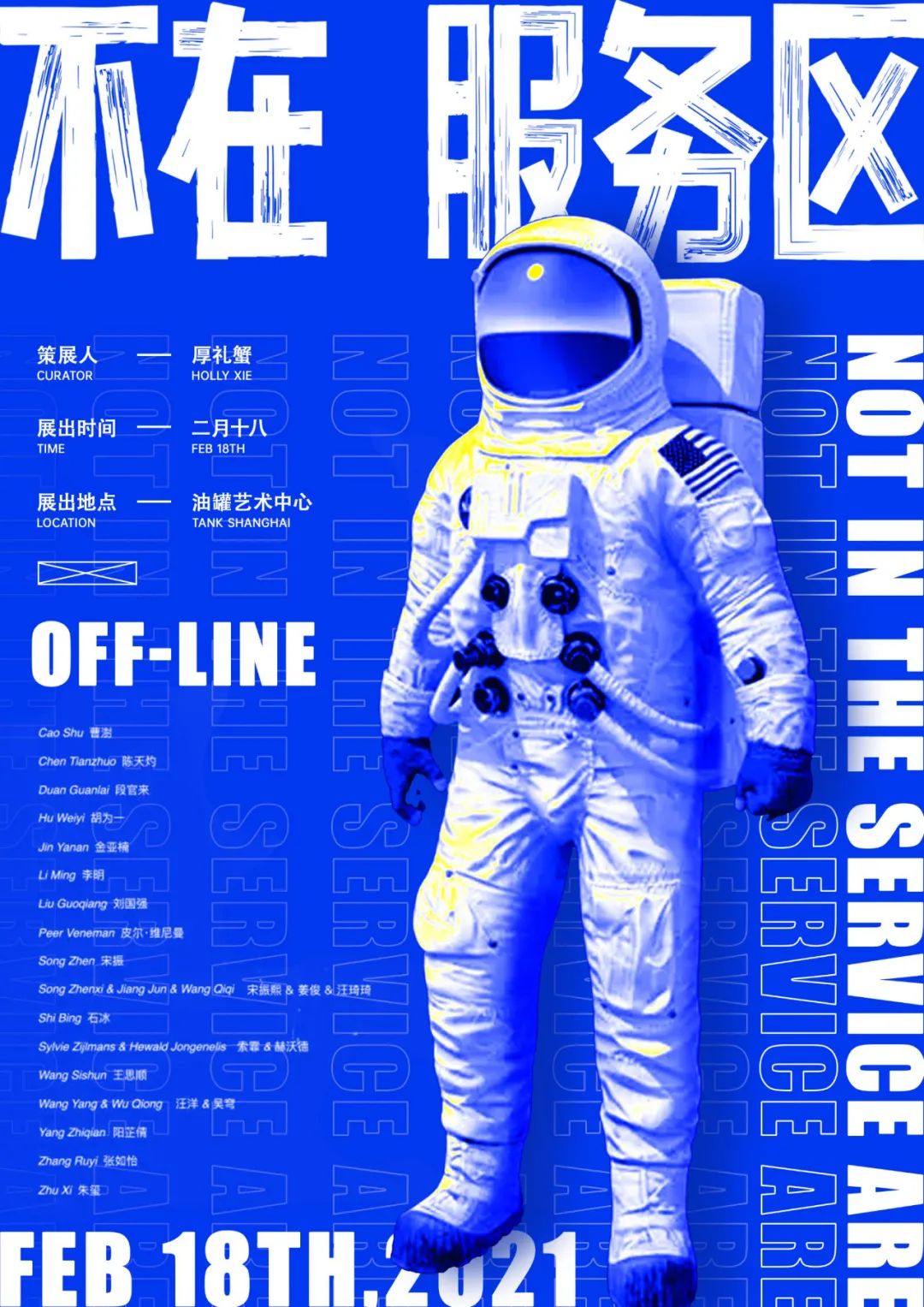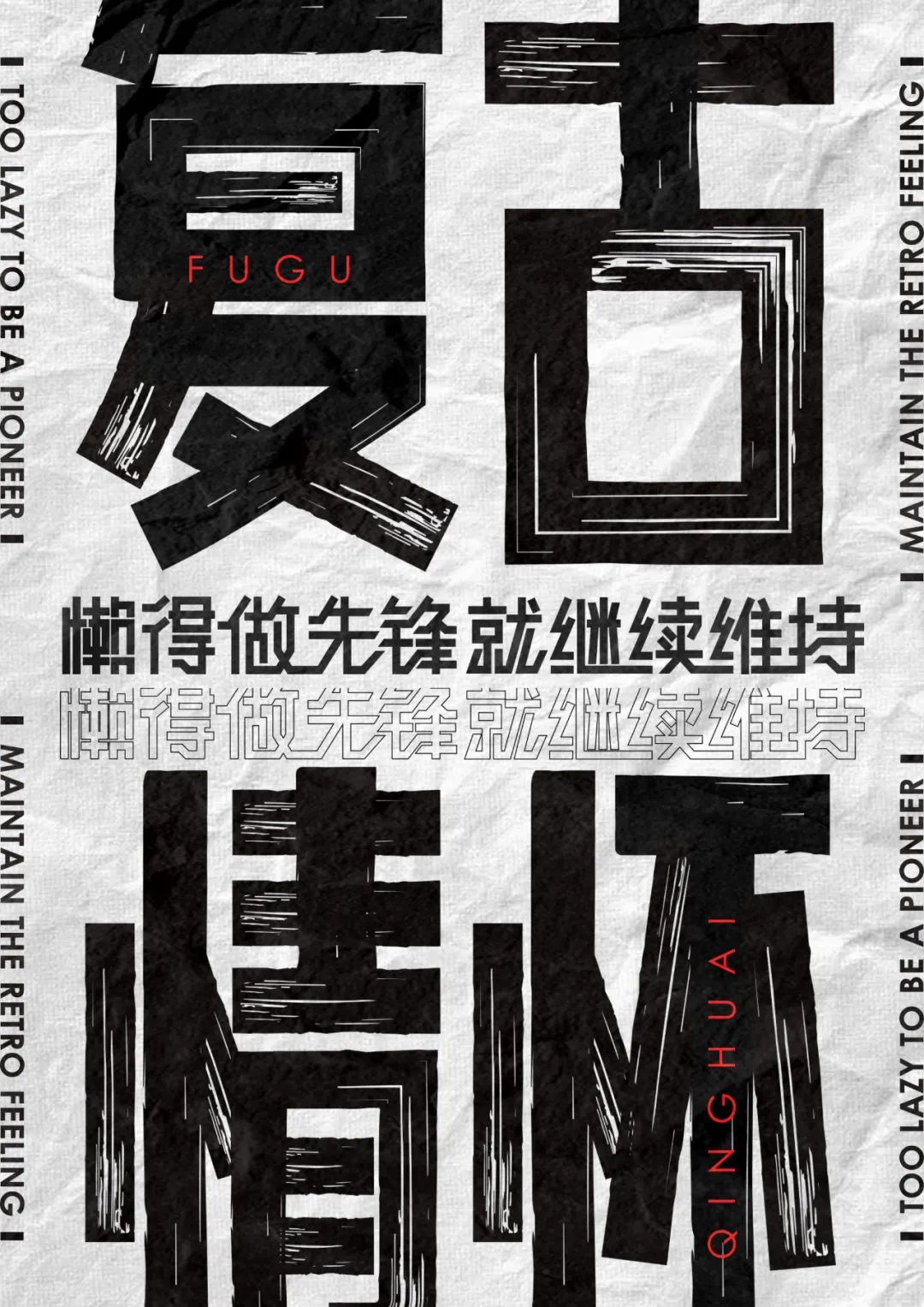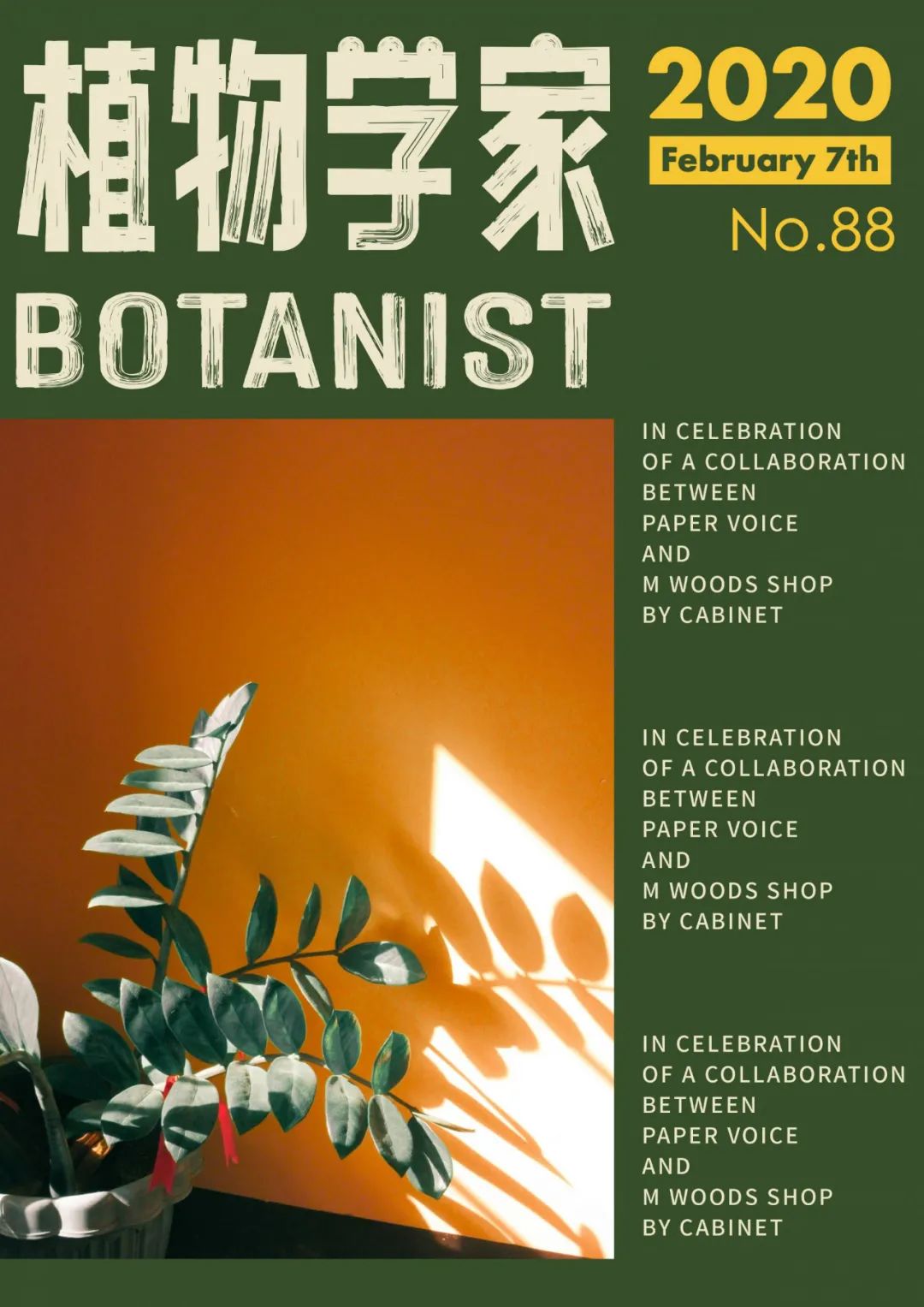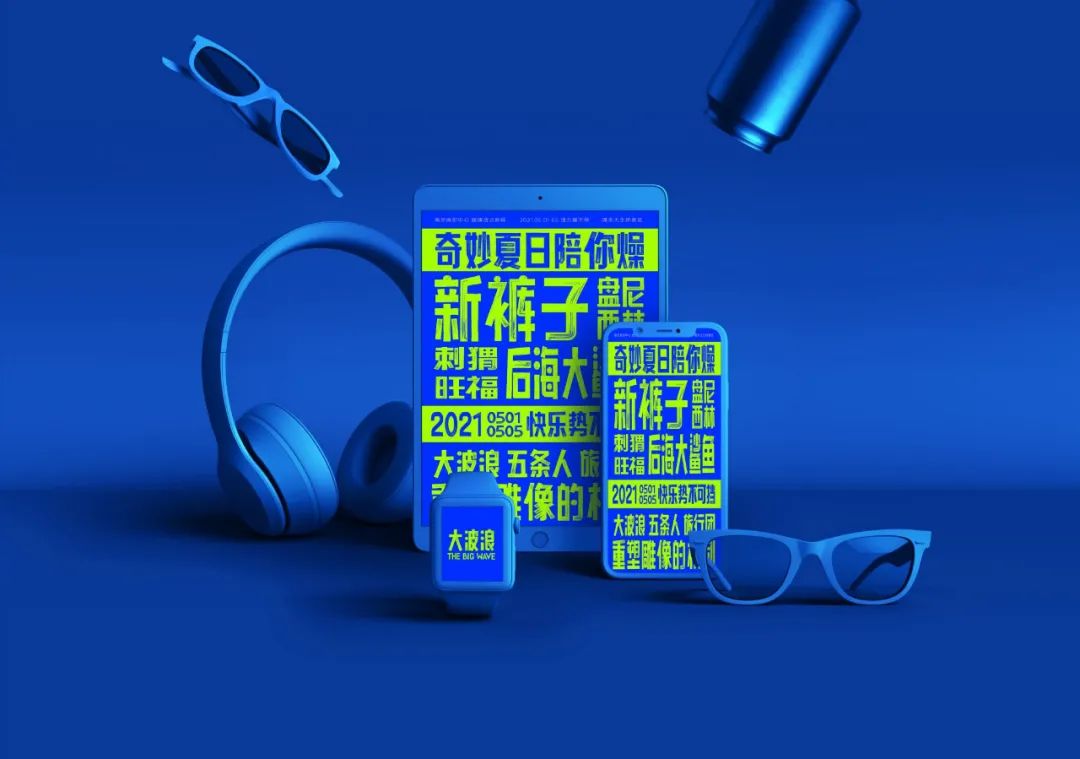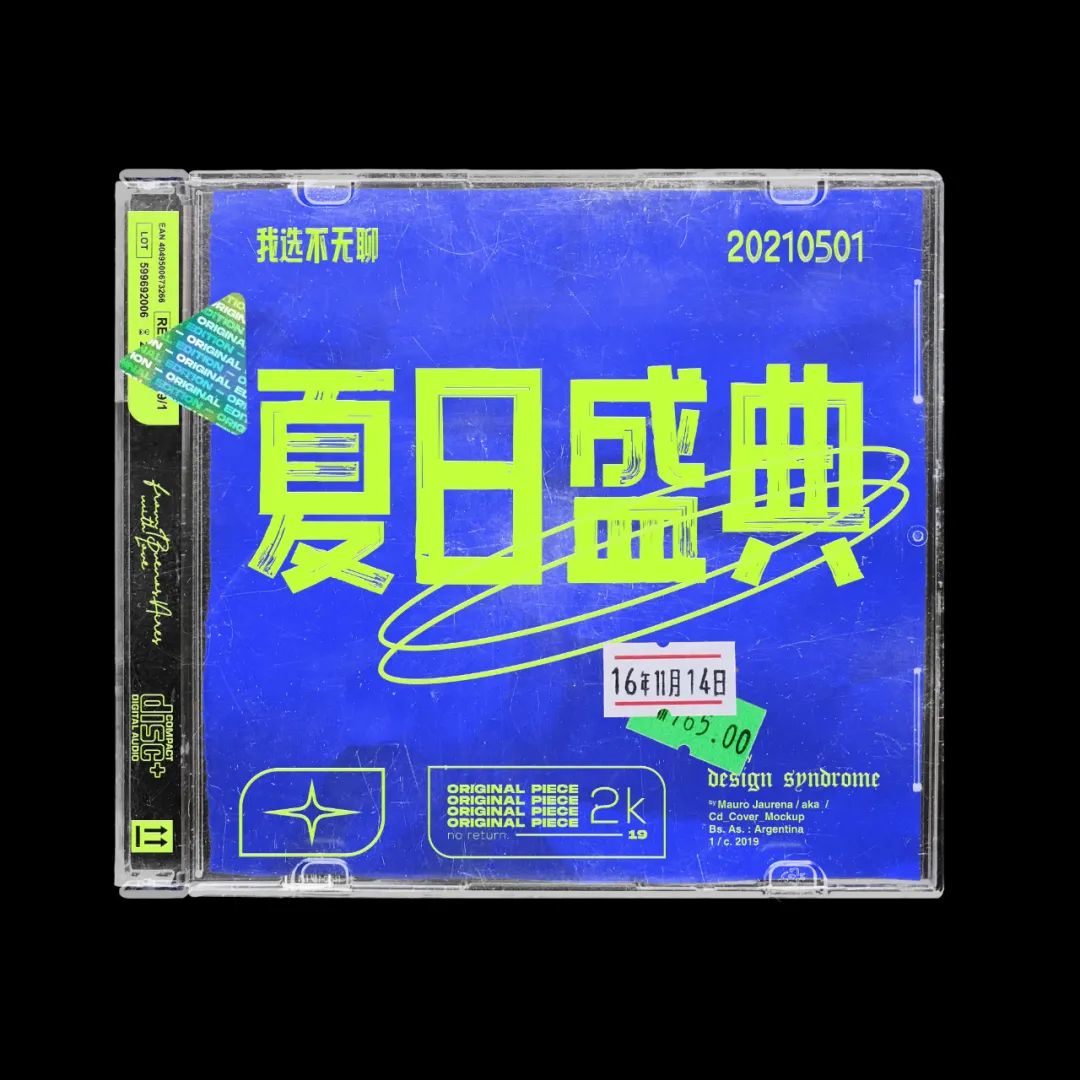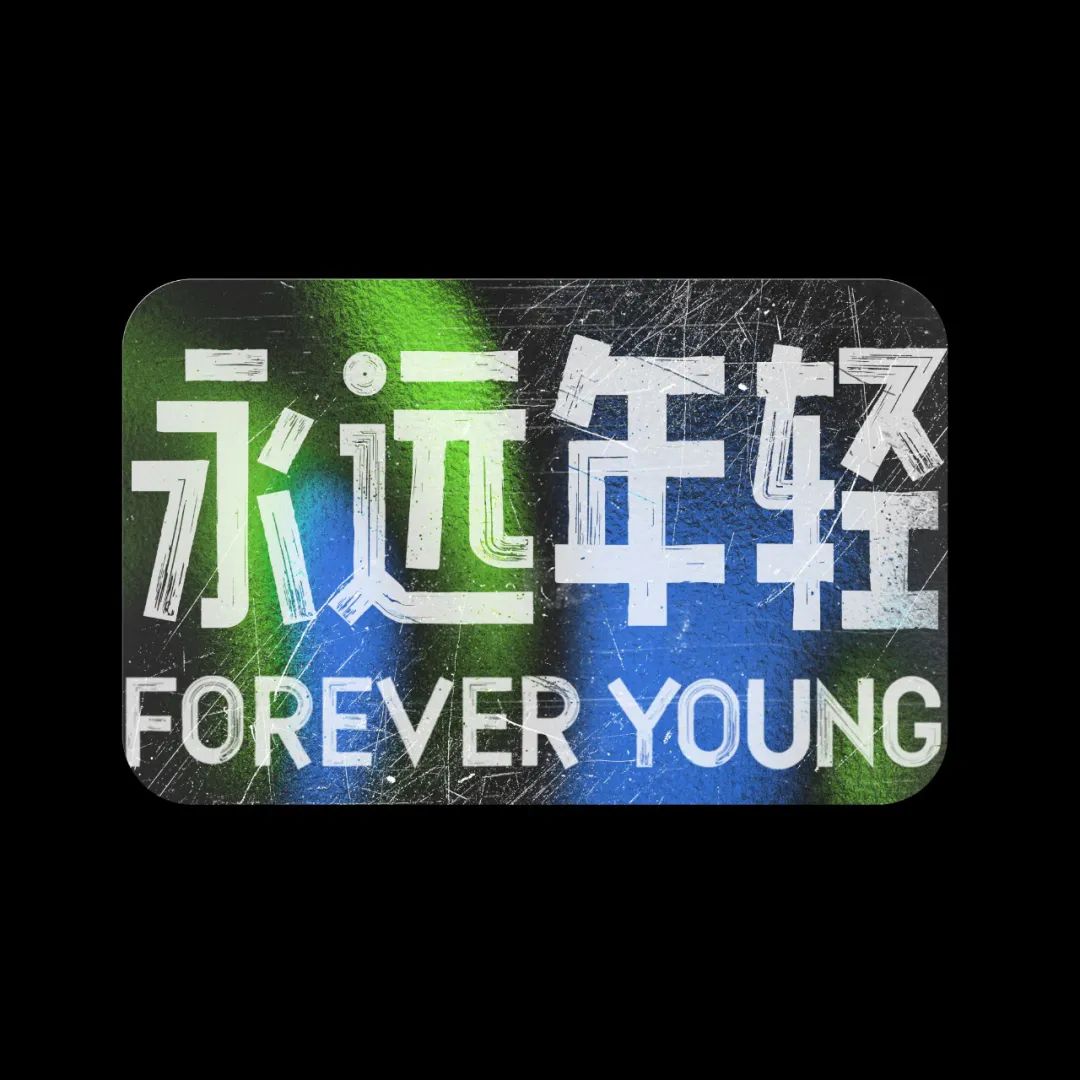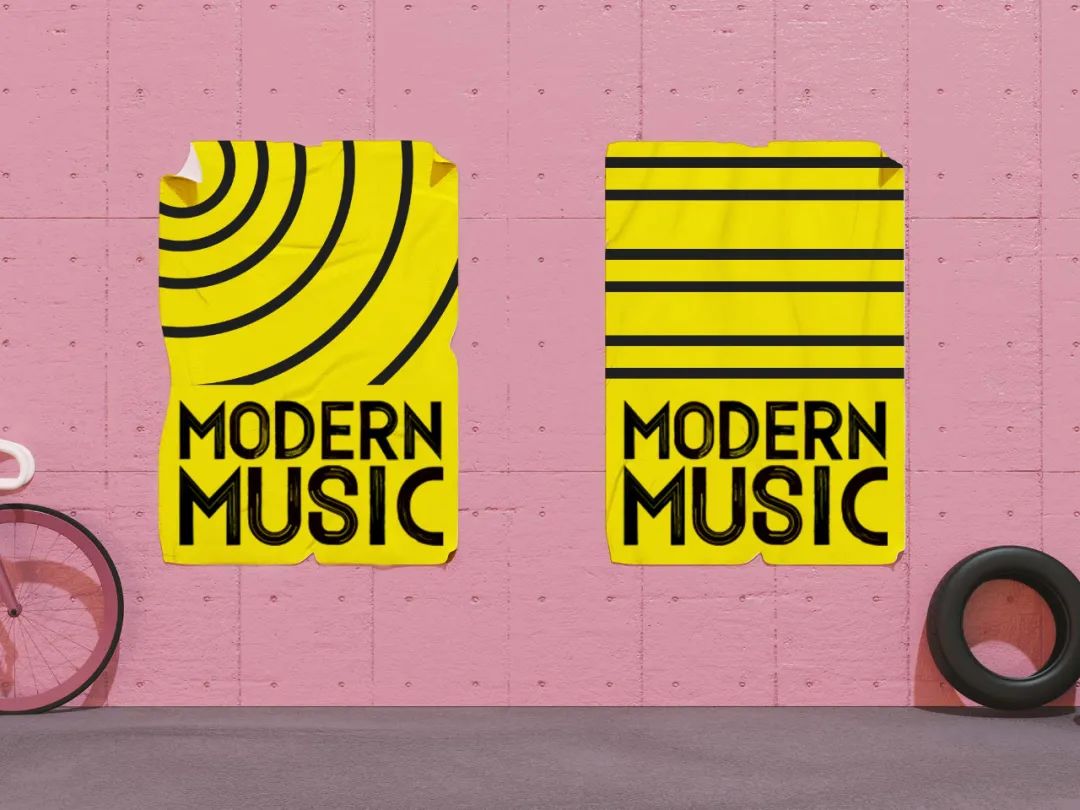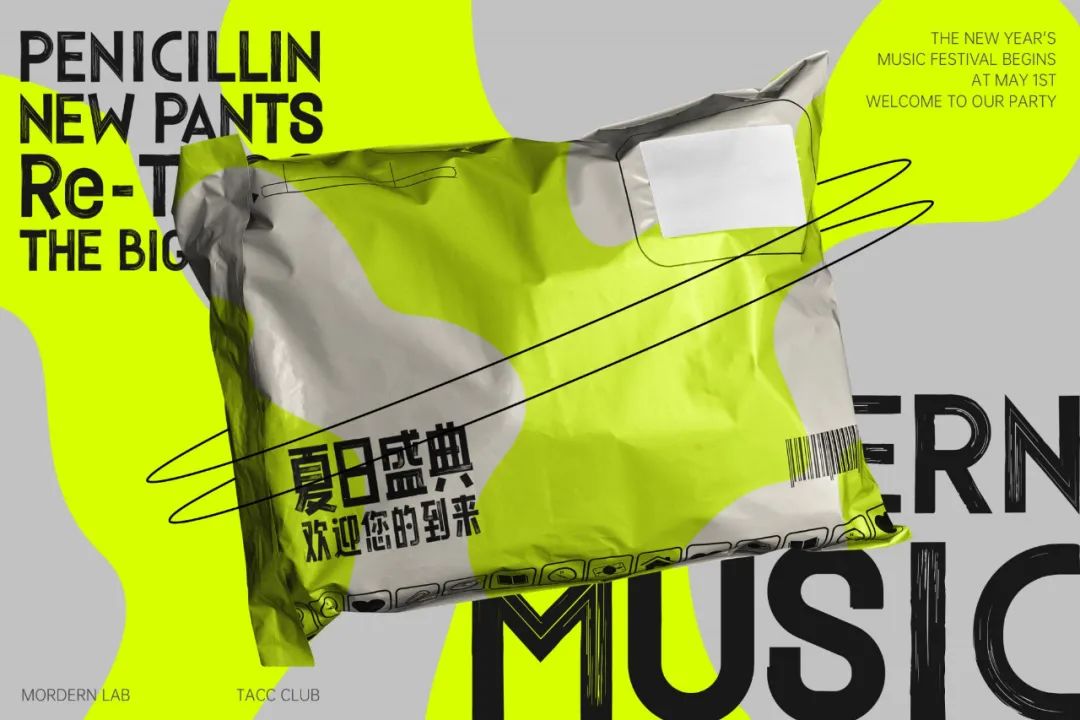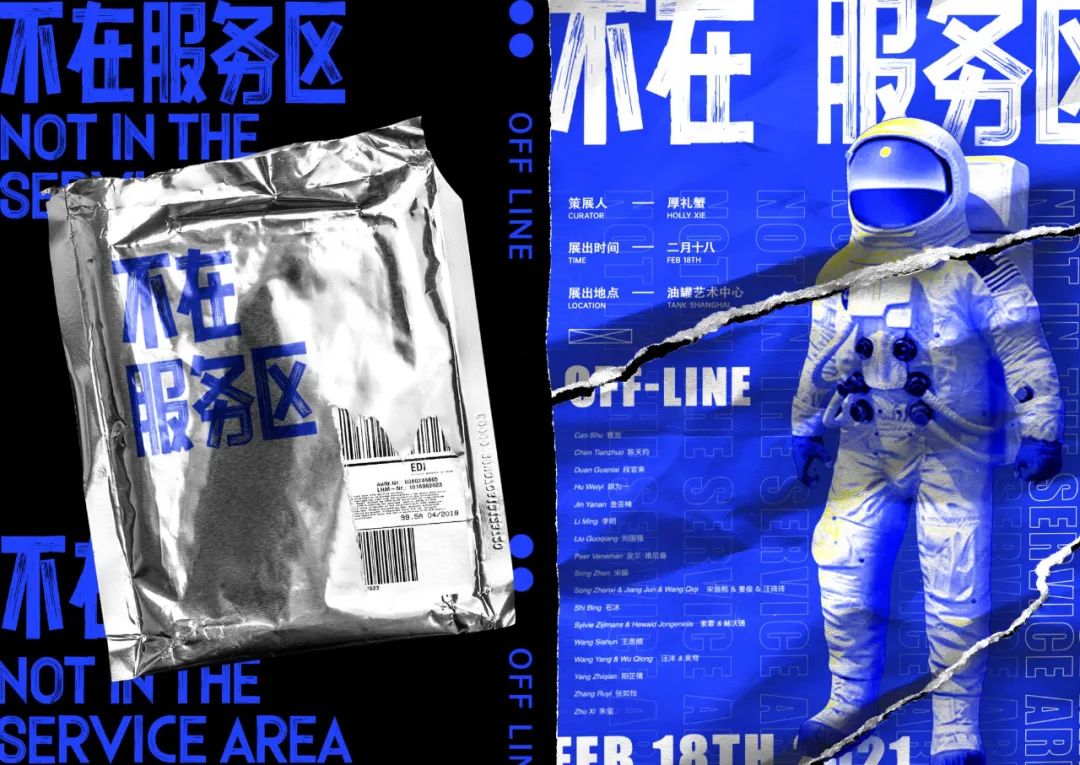
自带笔刷的字体推荐,笔刷字体有多好用
设计师都爱笔刷,因为它既可以丰富画面,也可以让字体一秒拥有“整容般”的效果。
只是有一个问题,就是找起来特别麻烦,特别是需要专属效果的时候,差一点就千差万别,所以这时候常常会选择自带“笔刷”的字体,比如字由上的这些:
都是英文,但我用得最多的却是中文,有没有那种自带“笔刷”,看起来就很与众不同的字体呢?必须有!柚子今天就想跟你们推荐最新的会员字——点字油漆体。
这是字由会员第一款涂鸦感字体,就像它的名字一样,是可以直接“刷”在画面上的,非常适合潮流感和复古气息的海报,很有视觉张力和艺术独特性,不信你康……